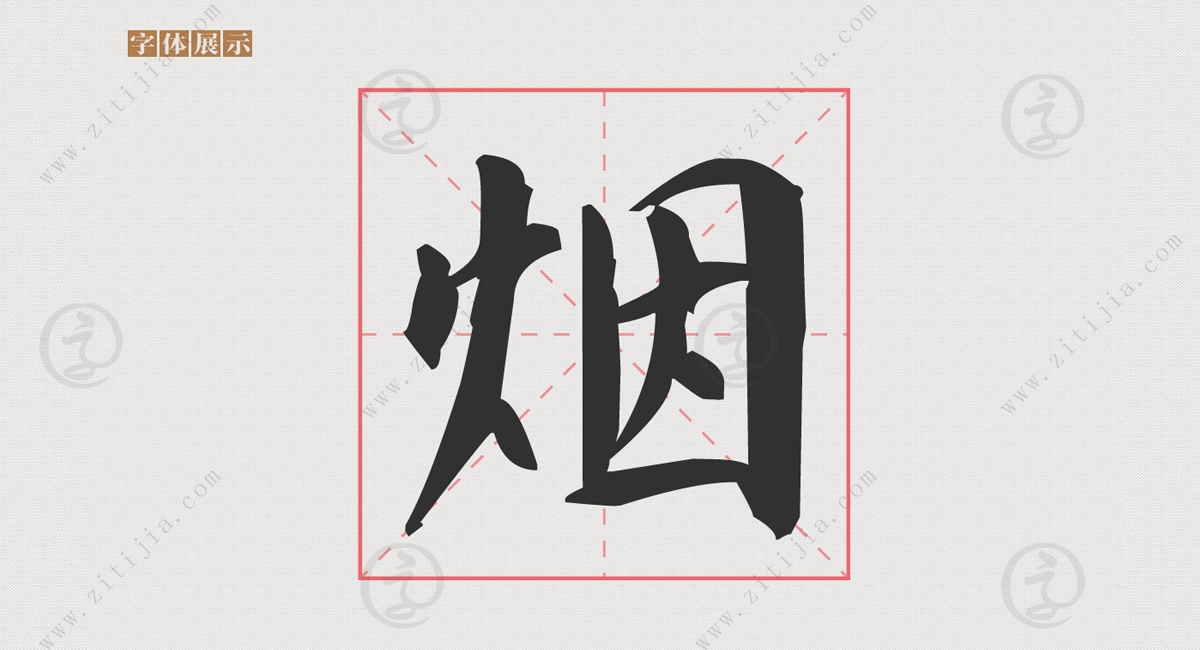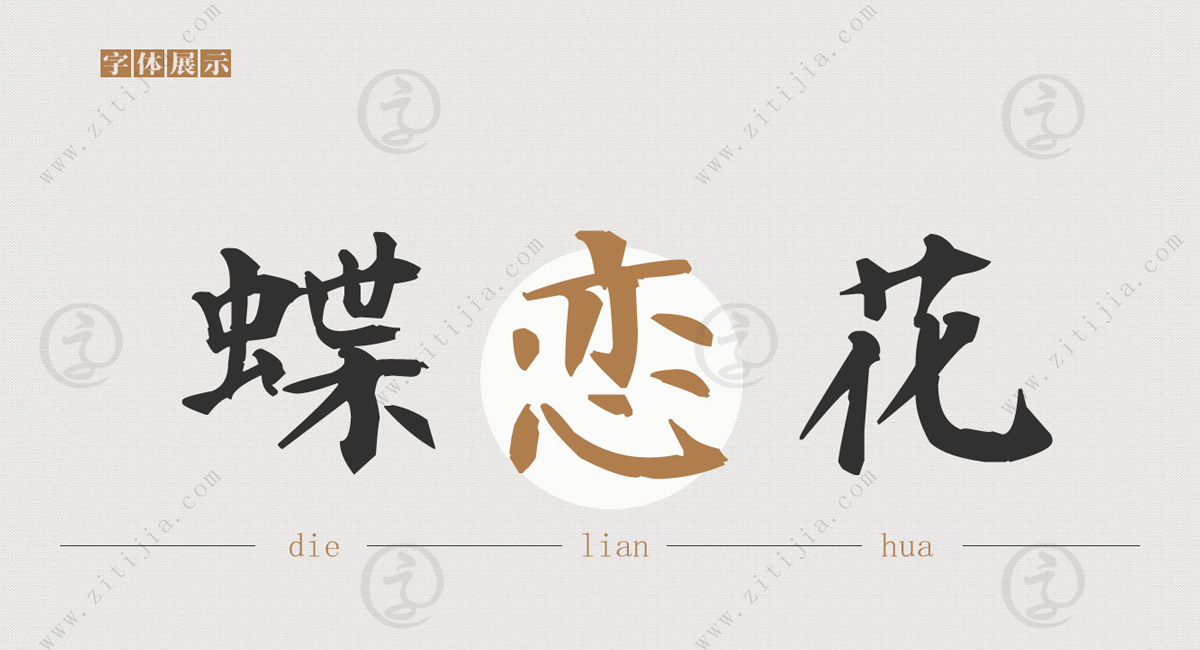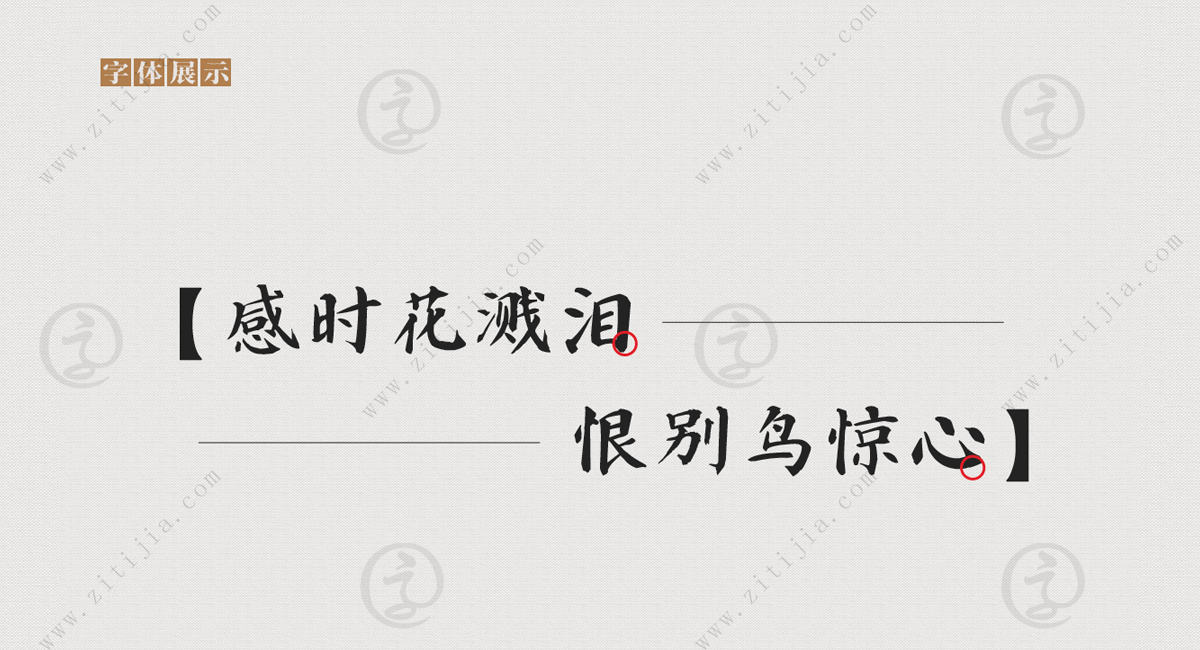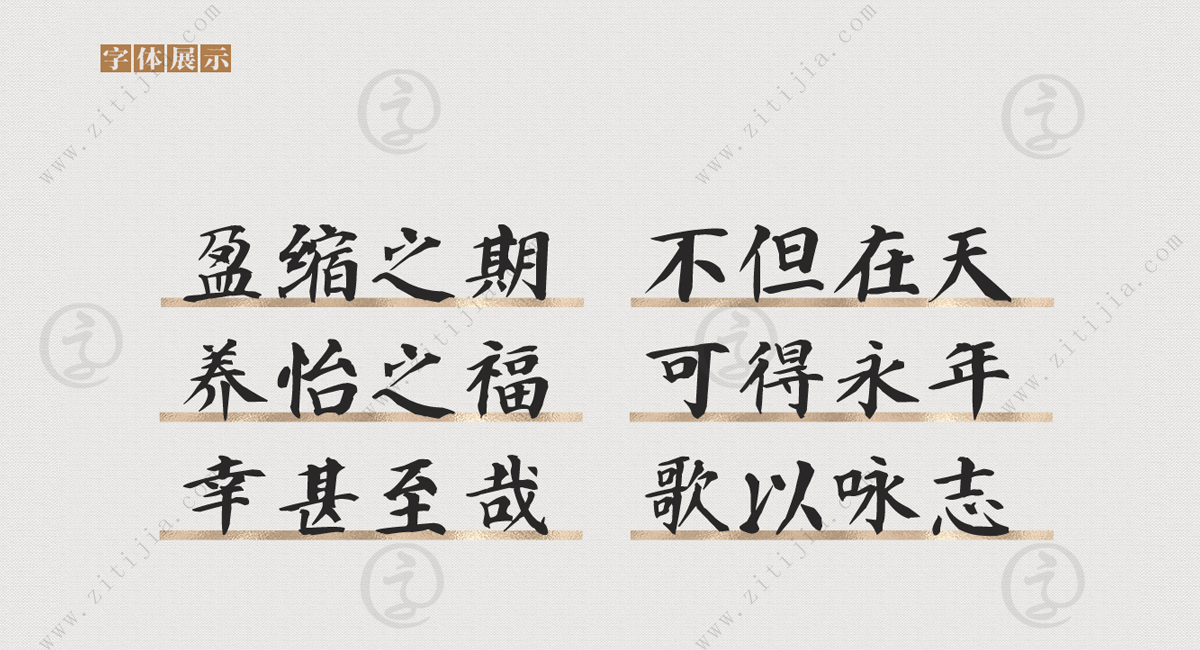
南构黄年虎楷书│每个字都具有独特的韵味和美感
南构黄年虎先生是当代著名的书法家,他的楷书字体以行草见长,展现出独特的艺术风格。黄年虎先生借鉴了二王(王羲之、王献之)的笔势,将其融入自己的创作中,使得他的作品既有传统的庄重与古拙之美,又不乏现代的灵动与活泼之感。
黄年虎先生在章法布局方面展现了独到的见解和才华。他善于运用空白与实字的对比,使得作品的整体呈现出一种舒展而有力的节奏感。他擅长运用线条的变化和错落有致的布局,使得每个字都呈现出鲜明的个性与动感。同时,他对于字形的处理也非常细腻,每个笔画都经过精心的雕琢,使得每个字都具有独特的韵味和美感。
黄年虎先生的楷书字体不仅仅是对传统的继承和发扬,更是在传统的基础上进行创新与突破。他的作品既有传统楷书的庄重与古拙之美,又融入了现代的灵动与活泼之感,展现出一种独特的艺术风格。他的作品不仅字体工整,结构严谨,还融入了他对于生活的独特感悟和情感的表达,使得每个字都充满了生命力和情感力。
黄年虎先生的楷书字体作品在书法界备受赞誉,他的作品不仅在国内享有盛誉,也受到了国际上的高度关注。他的作品常常被用于展览和收藏,成为书法爱好者和收藏家追逐的宝贵艺术品。他的楷书字体不仅仅是一种艺术形式,更是一种文化的传承和表达,展现了中国传统文化的独特魅力和艺术的无穷魅力。
总之,南构黄年虎先生的楷书字体以行草见长,取二王笔势,融历代大家书风,在章法布局方面颇有见地。他的作品既传承了传统的书法艺术,又融入了现代的创新与突破,展现出独特的艺术风格和个人风采。他的楷书字体作品不仅在国内外广受赞誉,也为中国书法艺术增添了新的辉煌篇章。
南构黄年虎楷书